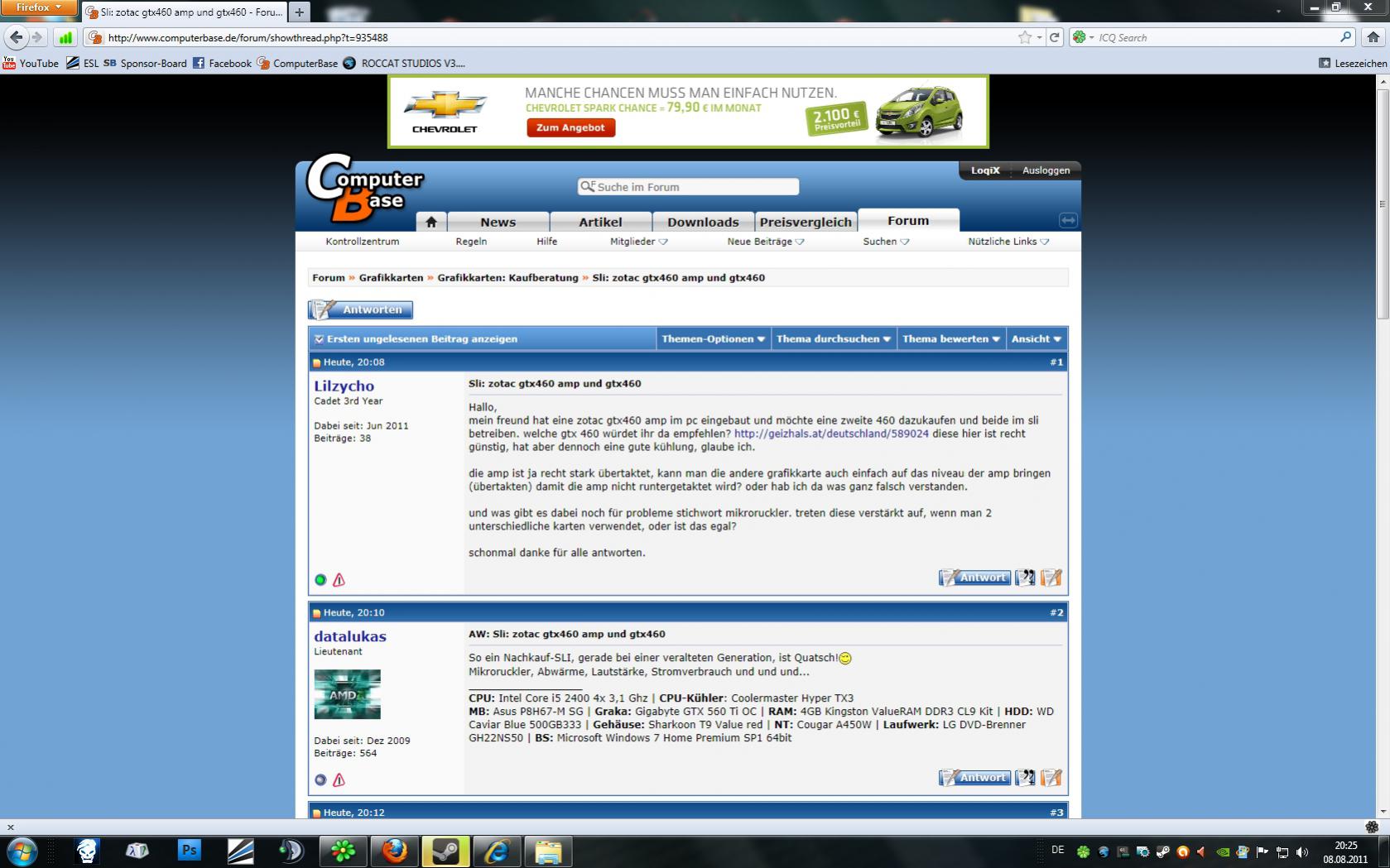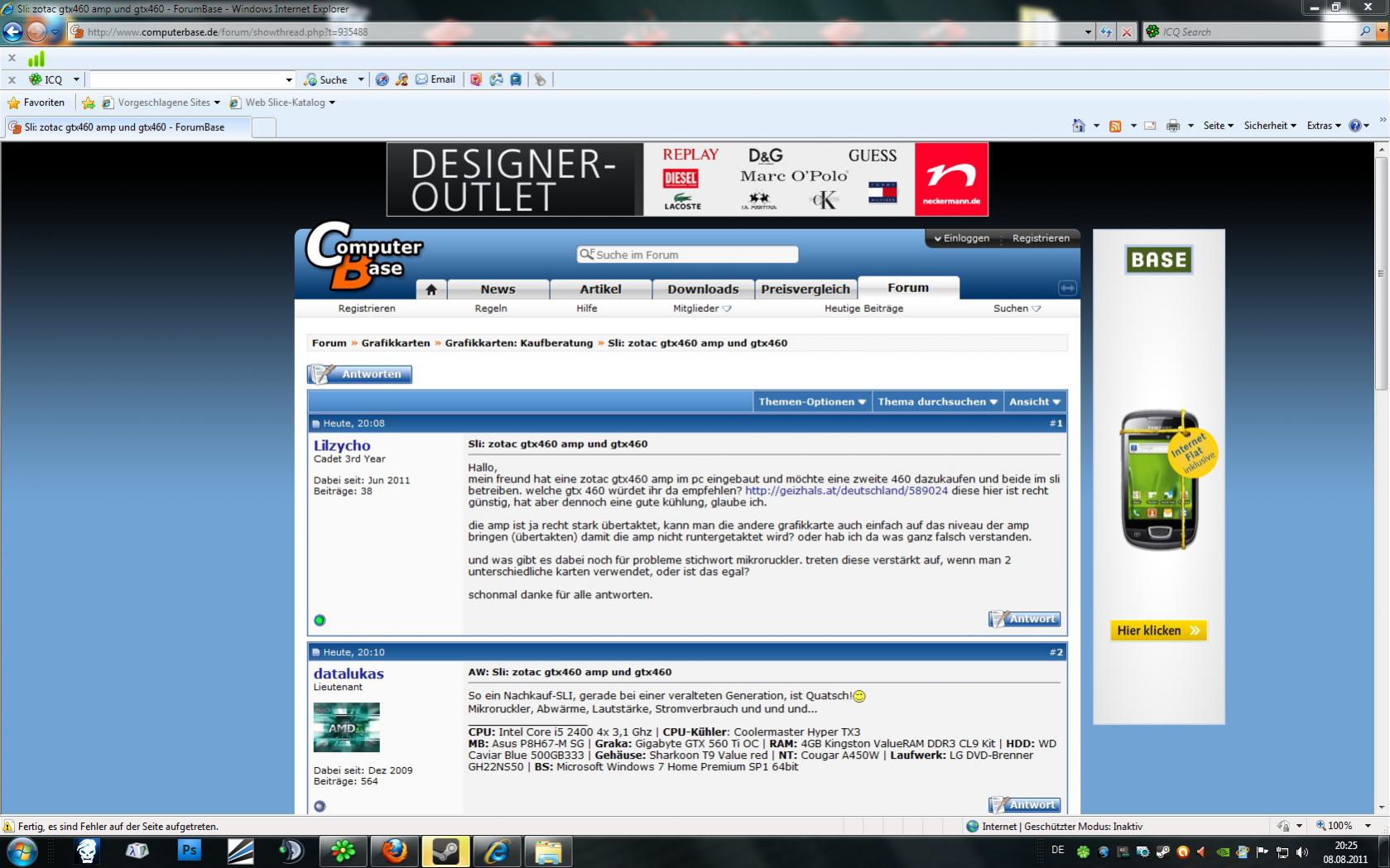
Firefox benutzt komische Schriftart
habe vor ein paar Tagen meinen neuen PC bekommen und natürlich direkt mal Mozilla Firefox installiert.
Mir ist aufgefallen, dass Firefox eine komische Schriftart benutzt, die mir garnicht gefällt.
Im Anhang findet ihr einmal die Schrift in Firefox und einmal die Schrift im Internet Explorer, die vom Internet Explorer würde ich auch gerne im Firefox verwenden.
optionen: standard-schriftart -> da stellst du um!
Also so sehr ich mich bemühe kann ich keinen Uterschied (außer Werbung) in der Darstellung der Webseite ausmachen.
Bei der Internetexplorer Sicht ist die Schrift etwas "verschwommen". Soweit ich weiß ist das ein Windows "Feature", aber ich weiß leider nicht wie es heißt. Mich würde es eher stören, ich mag die "scharfe" Schrift mehr.
Hardware-Beschleunigung in den Einstellungen ausschalten.
extras / einstellungen / inhalt / schiftarten & farben, da dann times new roman einstellen.
Schade, dass man den Unterscheid auf den Bildern nicht so gut erkennt, sry!
Habe das mit der Hardwarebeschleunigung abgestellt, leider hat sich nichts geändert.
Lol, habe nur das adblockplus Addon installiert und nun ist die Schrift wieder scharf.
Vielleicht hast du nach der Hardwarebeschleunigungsabschaltung (lol) keinen Neustart gemacht?